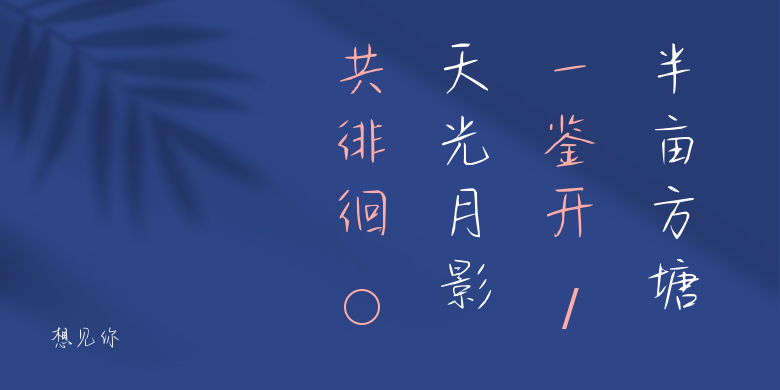
想见你
想见你,这款字体结构工整、笔画清晰,兼顾美观与易读性,适用于标题、正文、海报、包装、LOGO 等多种场景。字形优雅稳定,风格百搭耐看,适配日常排版与创意设计,让文字呈现更舒适、更具质感。想见你一笔一画,皆是细节,以均衡的比例、流畅的线条打造舒适视觉体验,字形端正大气,风格简约现代。无论是商业设计、品牌宣传还是日常排版,都能轻松驾驭,让文字更有格调与力量。想见你字体下载。